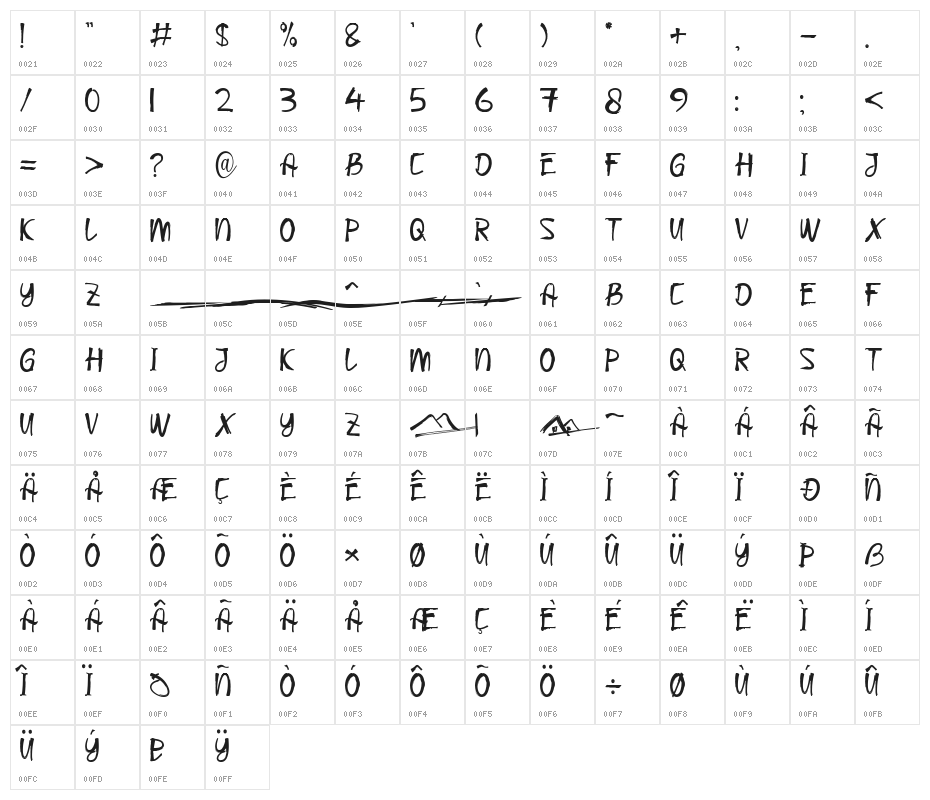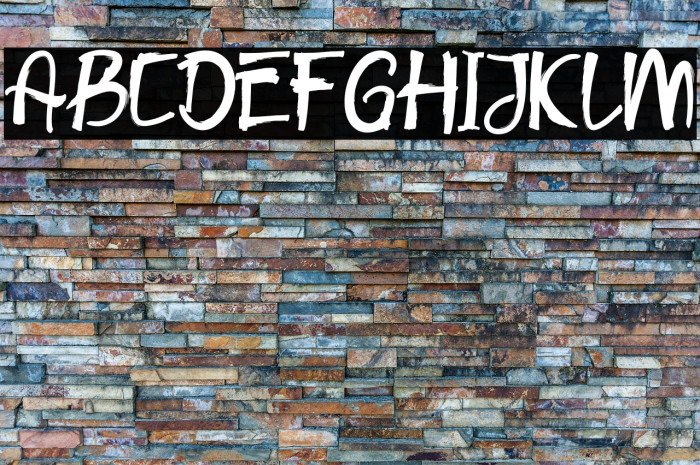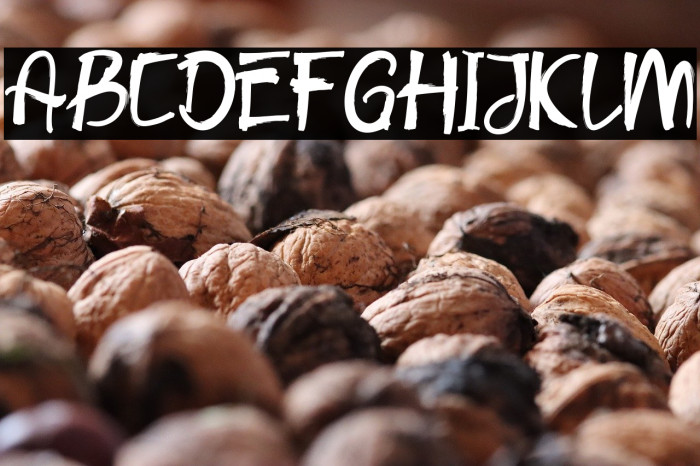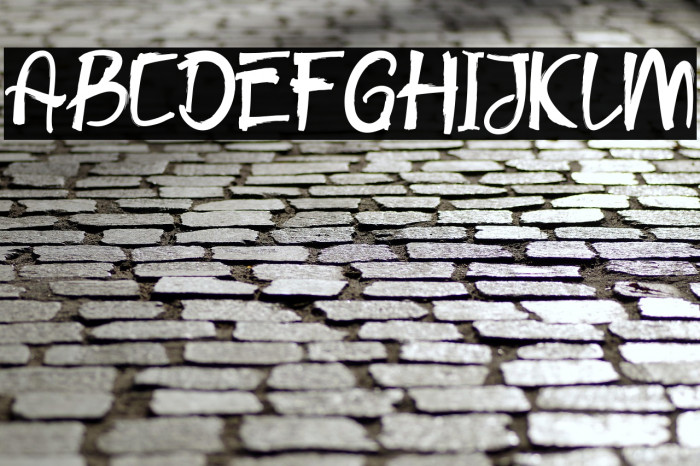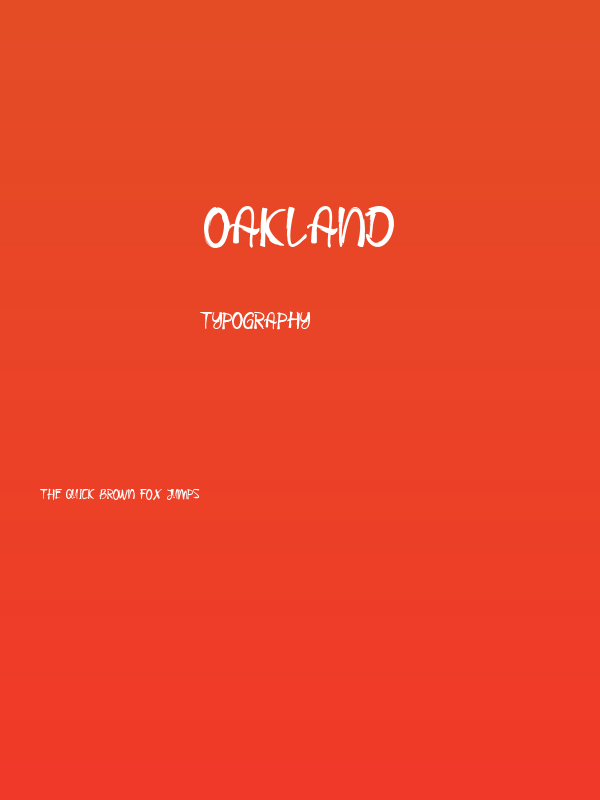
OAKLAND Font
✎ Thick
| Gesamtstil | Artistic, Casual |
| Vorgeschlagene Projekte | Perfect for posters, album covers, branding projects, and any design that needs a bold, artistic touch. |